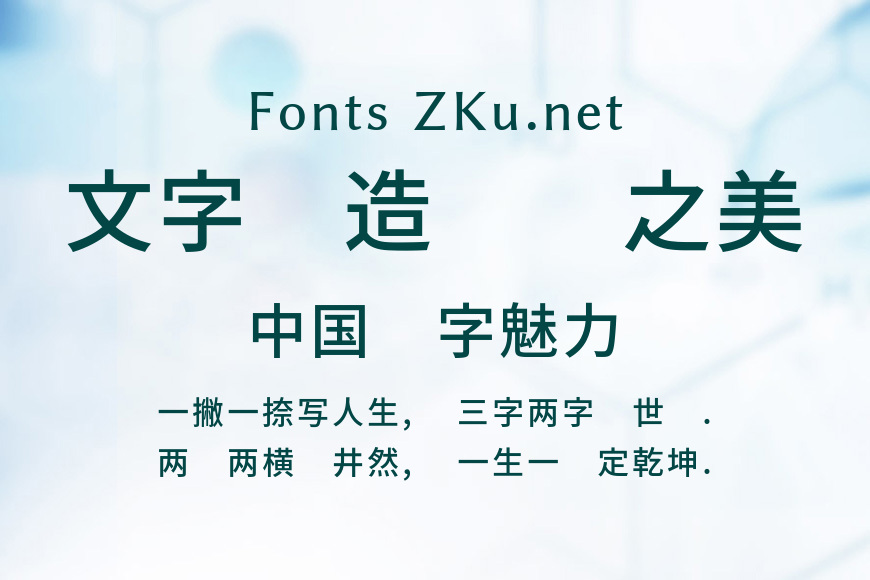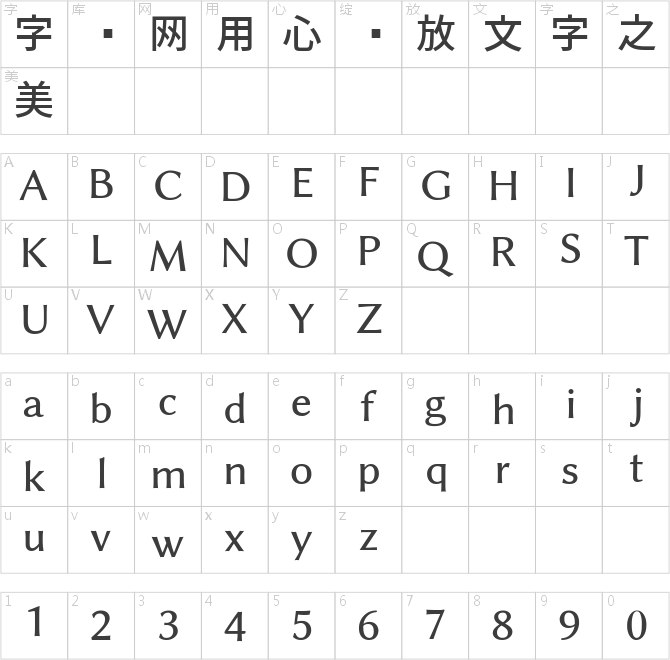
字体名称: 源暎漫画体
作者版权: おたもん
源暎漫画体
源暎漫画体是以日本版的思源黑体Semibold为基础,参考Light字重制作了平假名和片假名。因为骨骼来源于黑体字,所以在漫画台词中混合使用思源黑体、源真黑体等字体也可以毫无违和感地使用。这款字体削减了横笔的粗细,使字体看上去更具现代感。特别适合用于海报标题,LOGO等方面的设计。因为这个字体以面向漫画为主要用途,所以主要是与反映出的黑体汉字组合而成的“源暎漫画体”。